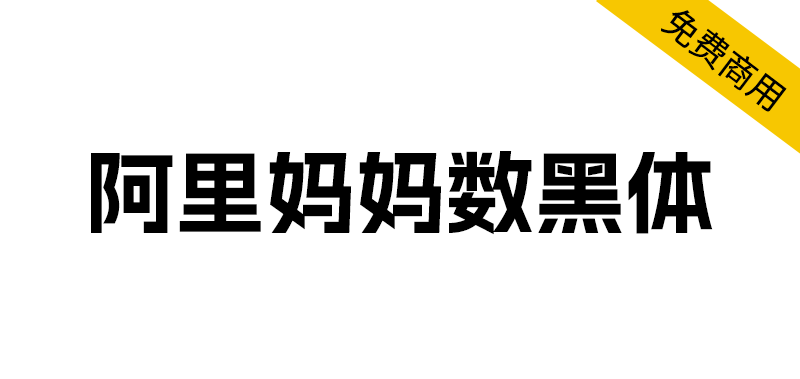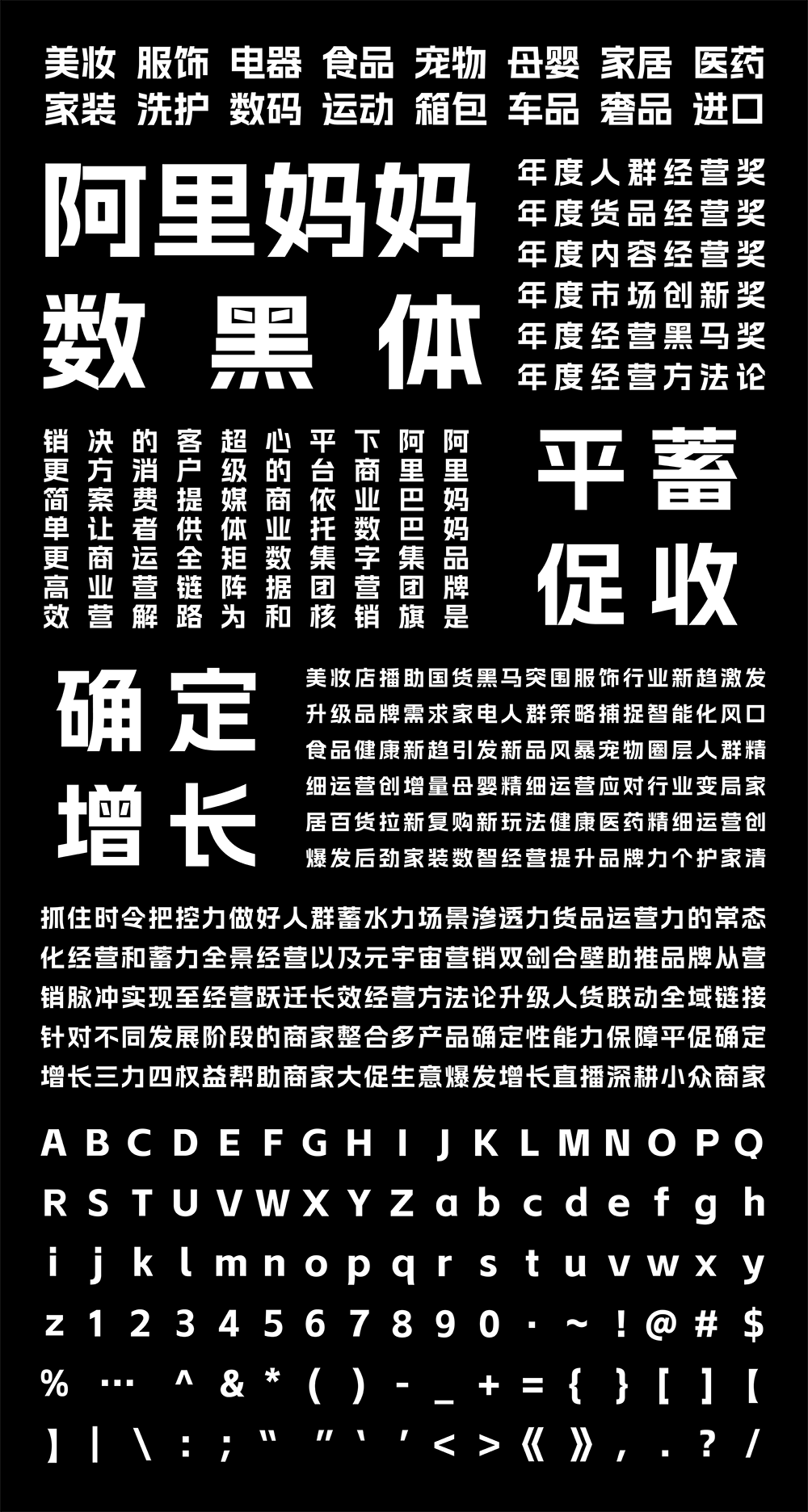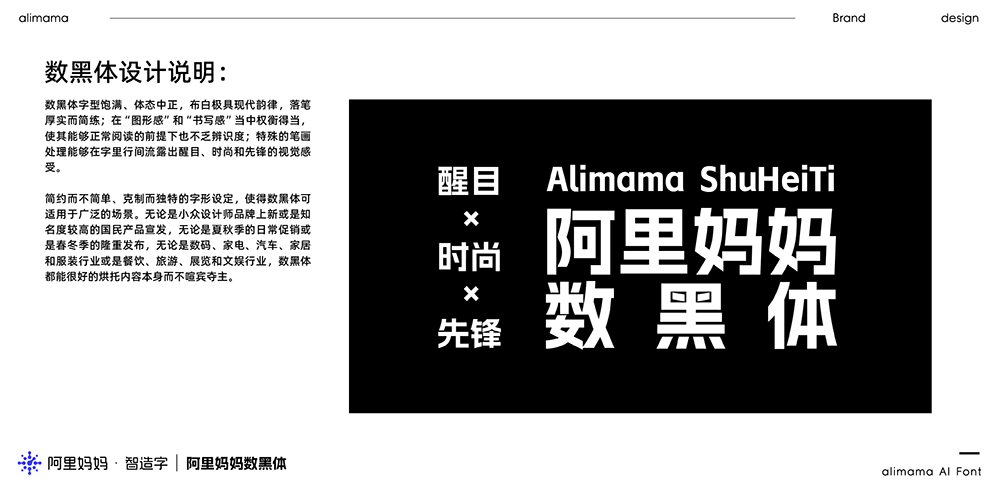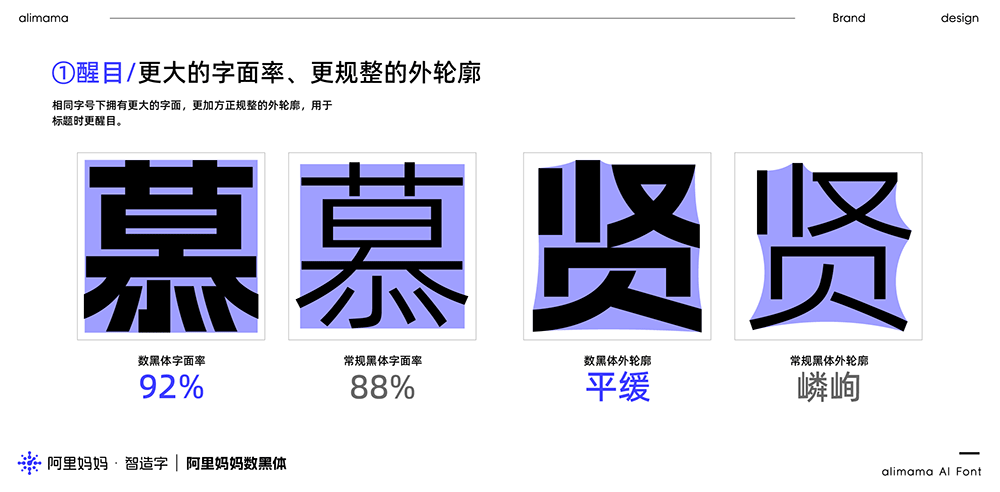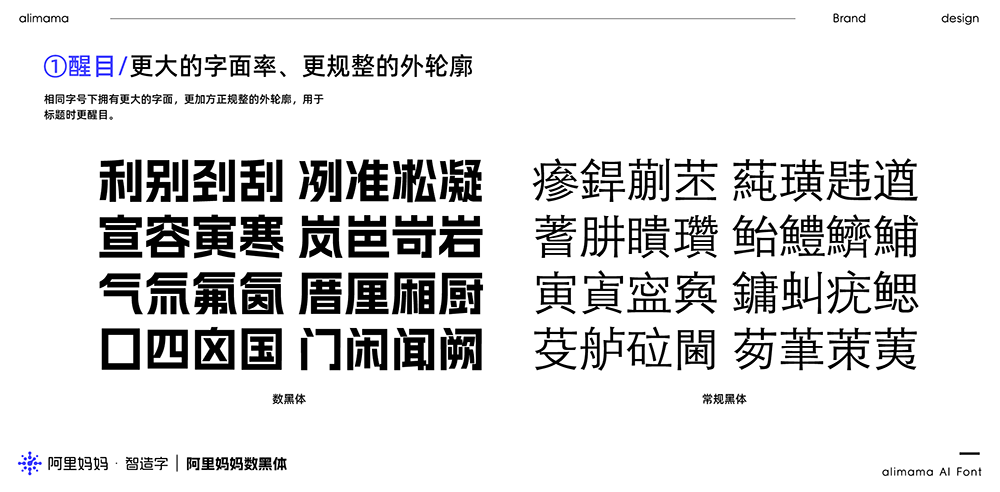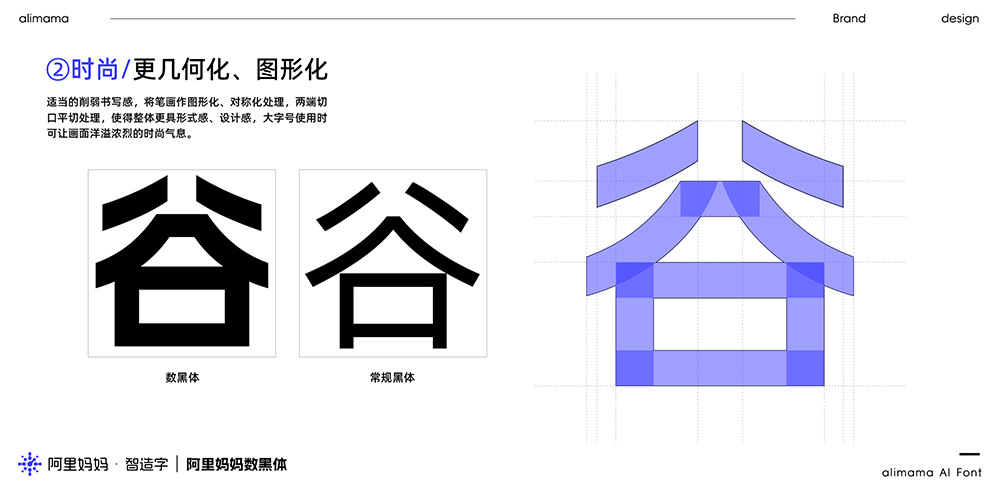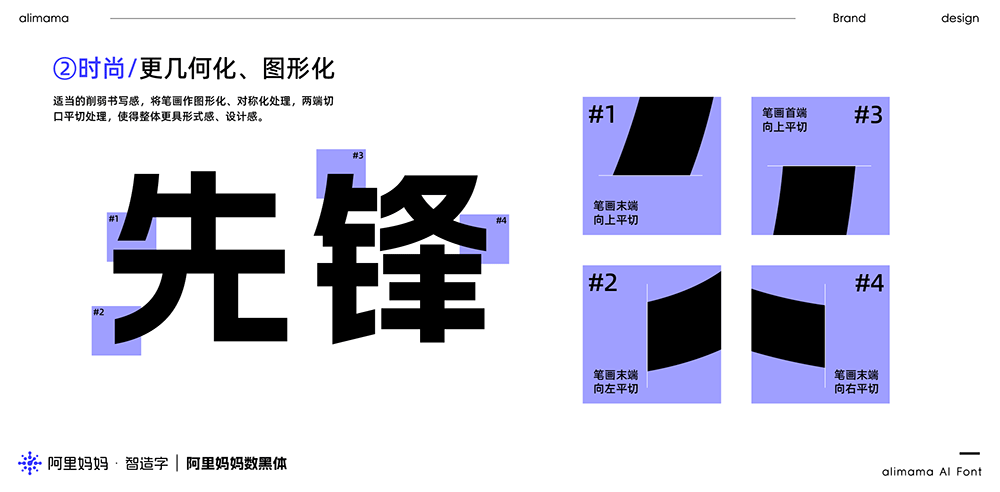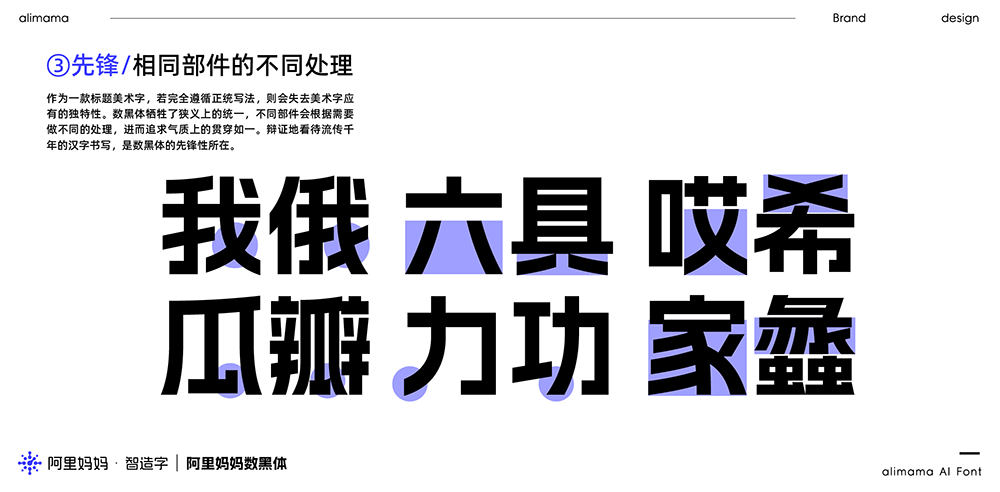
阿里妈妈数黑体是阿里妈妈·智造字自产自研打造了第一款AI字体产品。这款字的生成是人机协同工作的成果,设计原型,智能参与,人工干预,人机循环优化,直到最终生成满意标准字库。 数黑体是基于阿里妈妈营销应用场景下产生的营销字体,通用性和易用性强,适用于多品类商品,更高效的解决了电商类平台的用字需求。
阿里妈妈数黑体为简体字库,收纳的中文字符包括但不限于GB2312,共计6767个汉字;英文大小写共52个;常用标点符号共206个,总计7025个字符。 字型饱满、体态中正,布白极具现代韵律,落笔厚实而简练;字里行间流露出先锋、前卫和时尚的视觉感受。适用于电商、广告、品牌形象、推广物料等场景。